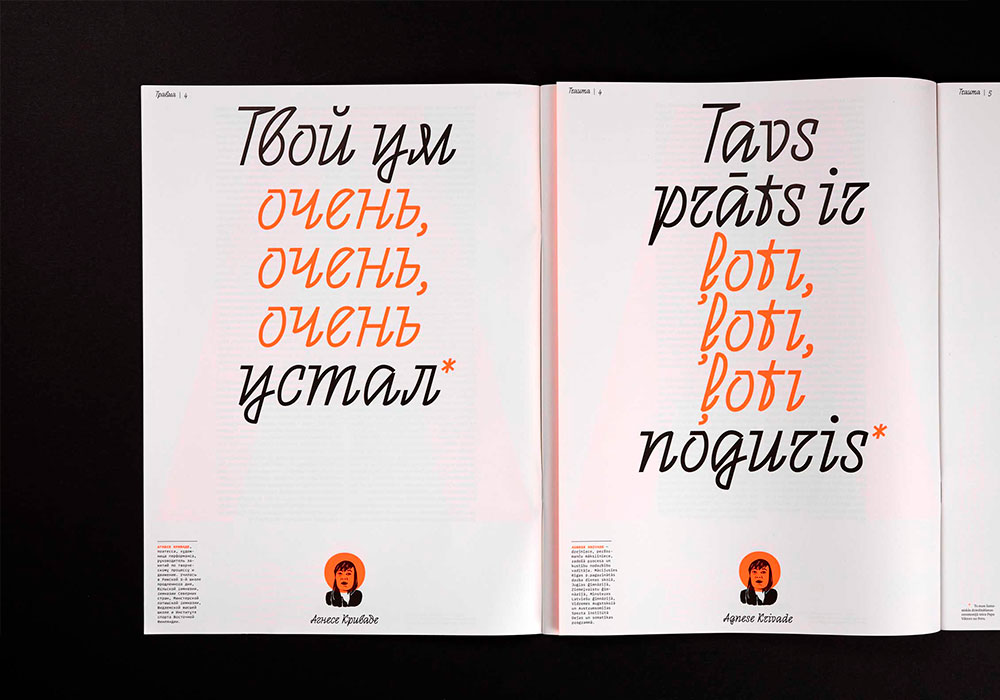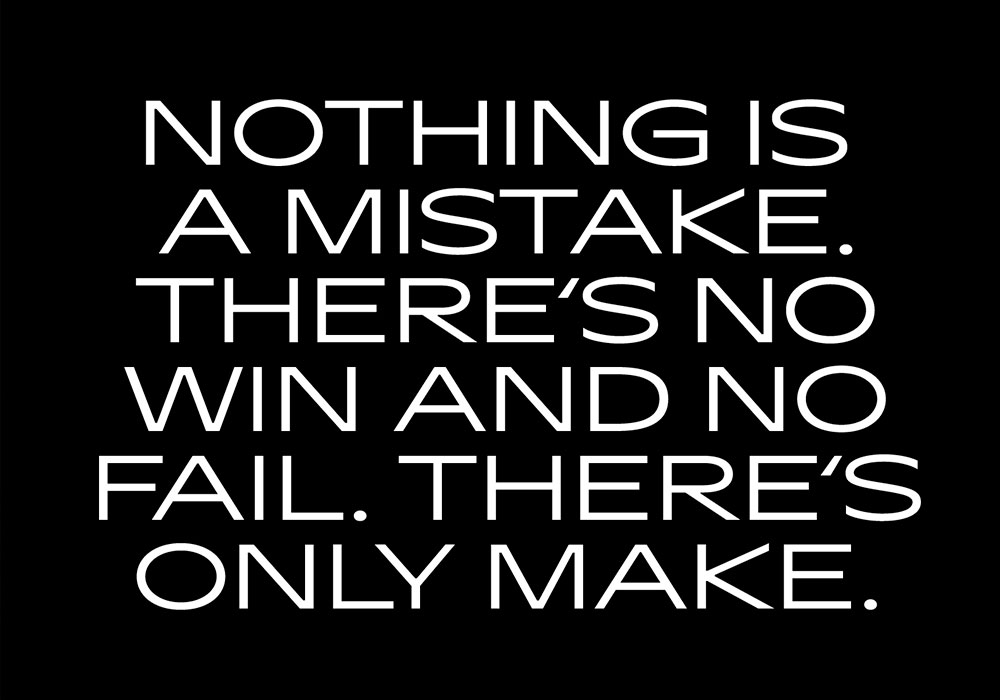
Tomorrow, el marketplace para tipografías experimentales de type.today, ofrece una amplia selección de fuentes tipográficas de calidad cuyo nexo en común es el afán rupturista, pero con los pies en la tierra. Por Ana Moliz.
La experimentación tipográfica es un mecanismo que encuentra su razón de ser en la búsqueda de los límites de lo posible. No se trata solamente de que seamos o no capaces de reconocer una letra —el recurrente debate sobre la legibilidad—, sino de determinar ese lugar conceptual en que una «a» deja de ser una «a» porque su aspecto se aleja en exceso de las convenciones tipográficas que hacen que el cerebro humano la reconozca como tal. Un lugar que, en caso de existir, variará de posición según a quién le preguntes.
Ni qué decir tiene que la tipografía, como herramienta de comunicación, debe responder fielmente a una serie de convenciones y reglas. A partir de esta idea generalmente aceptada, resulta perfectamente legítimo buscar la sorpresa, el asombro, la extrañeza, la ruptura. Explorar; ver qué hay más allá.
Por su propia naturaleza, el diseño gráfico y el diseño tipográfico son disciplinas sumamente dinámicas. Es natural y maravilloso que aparezcan nuevas corrientes y tendencias cada poco, y que haya profesionales que no teman el riesgo ni el error.
En este contexto aparece Tomorrow, el marketplace para experimentos tipográficos de type.today. En él se pueden encontrar fuentes tipográficas de muy diversos diseñadores y diseñadoras cuyo nexo de unión es ir más allá de la funcionalidad y tratar de descubrir ese nuevo lugar, o más bien lugares, por donde transitará el diseño de tipos en el futuro inmediato.
Y las cuestiones que se plantean en Tomorrow no se ciñen exclusivamente a las formas de las letras, sino que también abarcan su distribución y a asuntos de índole más especulativa como la evolución del concepto «fuente tipográfica» en los próximos años.
Al frente de type.today y Tomorrow encontramos a Ilya Ruderman y Yuri Ostromentsky, jóvenes diseñadores tipográficos, aunque ya acumulan una dilatada y rica experiencia profesional en el diseño y la dirección de arte, además de ser los creadores de la fundición tipográfica CSTM Fonts, especializada en fuentes cirílicas y latinas.
Un vistazo general a las fuentes presentes en Tomorrow revela un exquisito cuidado en la selección de las mismas, todas ellas de aliento rupturista y desprejuiciado, pero sin llegar al paroxismo formal ni al experimentalismo sin base alguna.
En Tomorrow encontramos un abigarrado conjunto de fuentes, donde, puestos a destacar, nos fijamos, por ejemplo, en CSTM Xprmntl 03, diseñada por el propio Ostromentsky. Se trata de una fuente variable en donde el lejano pasado de las letras góticas y unciales rusas juega a entrelazarse y combinarse gracias a las posibilidades técnicas que ofrece el diseño tipográfico digital contemporáneo, abriendo con ello el camino hacia estimulantes y sorprendentes implementaciones visuales.
Tomorrow es un excelente espacio de inspiración tipográfica que ampliará nuestras referencias visuales. Esperamos que vaya sumando nuevas fuentes de tanta calidad y frescura como las que ahora se pueden encontrar.